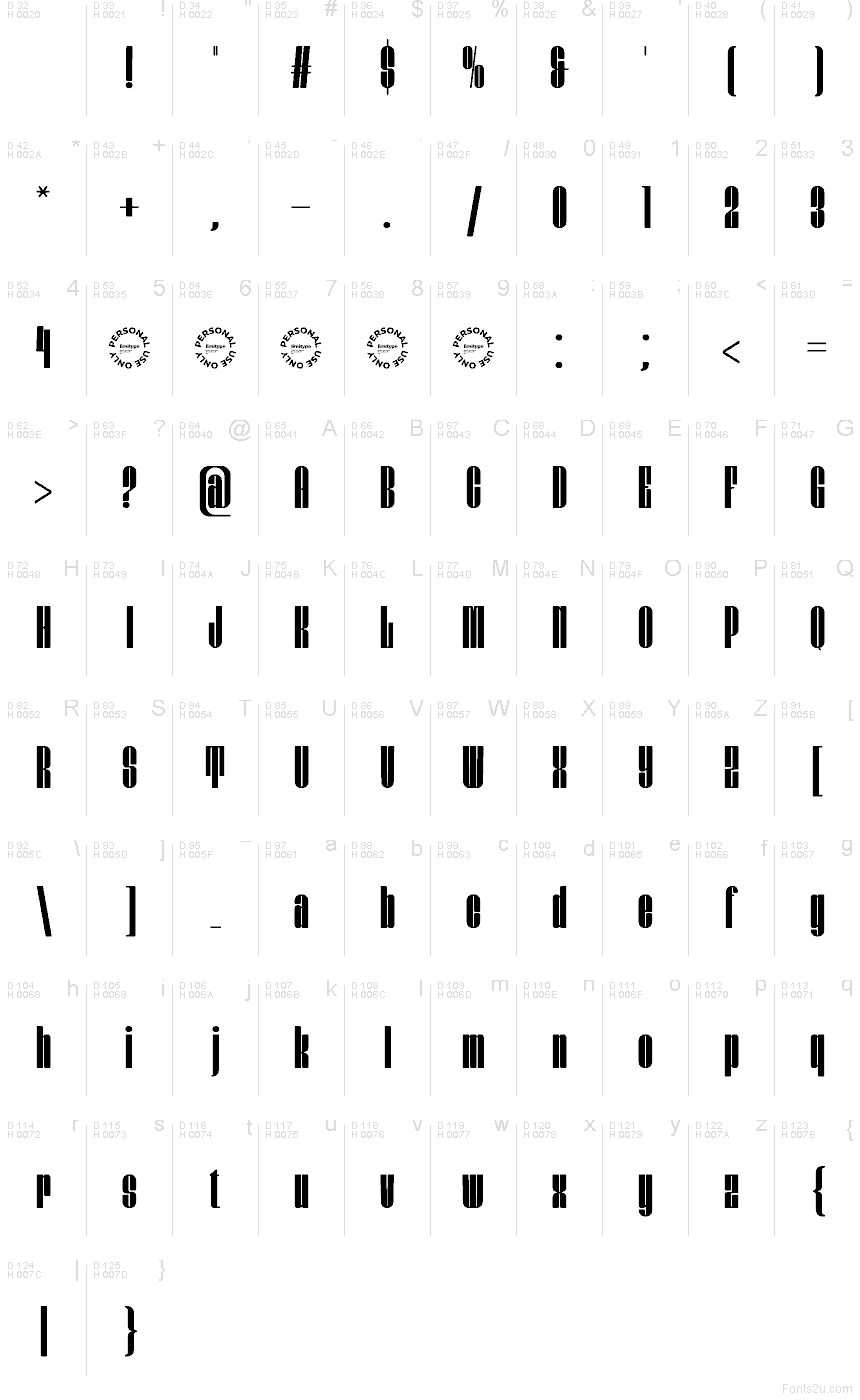
Granetha da Limitype é uma fonte display retro gratuita com um toque elegante de Art Déco. As letras são extremamente altas e estreitas, com cantos arredondados e longos traços verticais que tornam o design elegante, teatral e um pouco nostálgico, como a sinalização de cinemas antigos.
Encaixa-se naturalmente em títulos de cartazes, capas de álbuns, menus de cocktails, embalagens boutique e identidades de eventos onde poucas palavras transmitem o ambiente. Como fonte gratuita, a Granetha Demo é ideal para manchetes curtas, cabeçalhos e cartões de título, pois as suas formas alongadas criam um ritmo forte sem precisarem de muito texto.